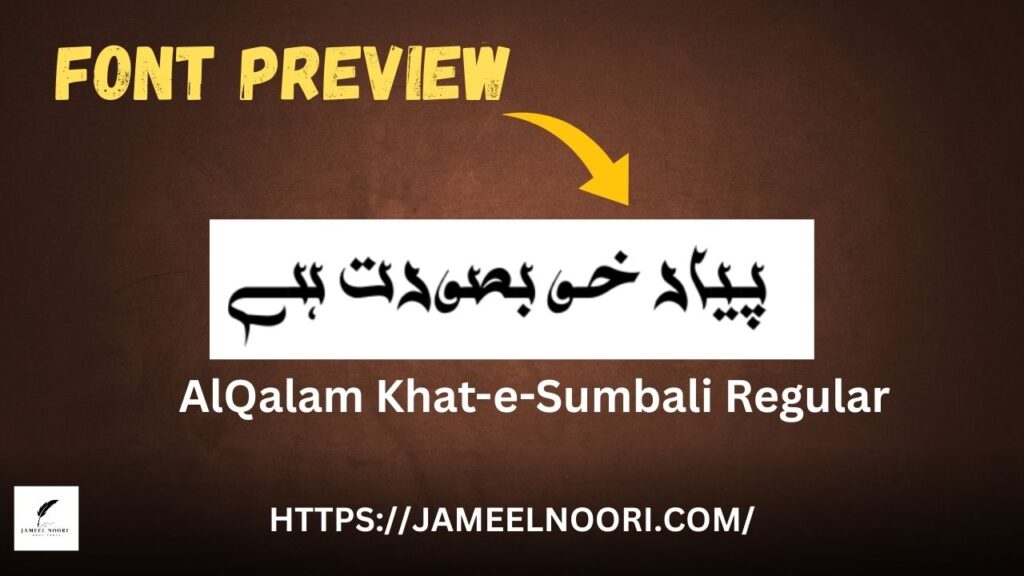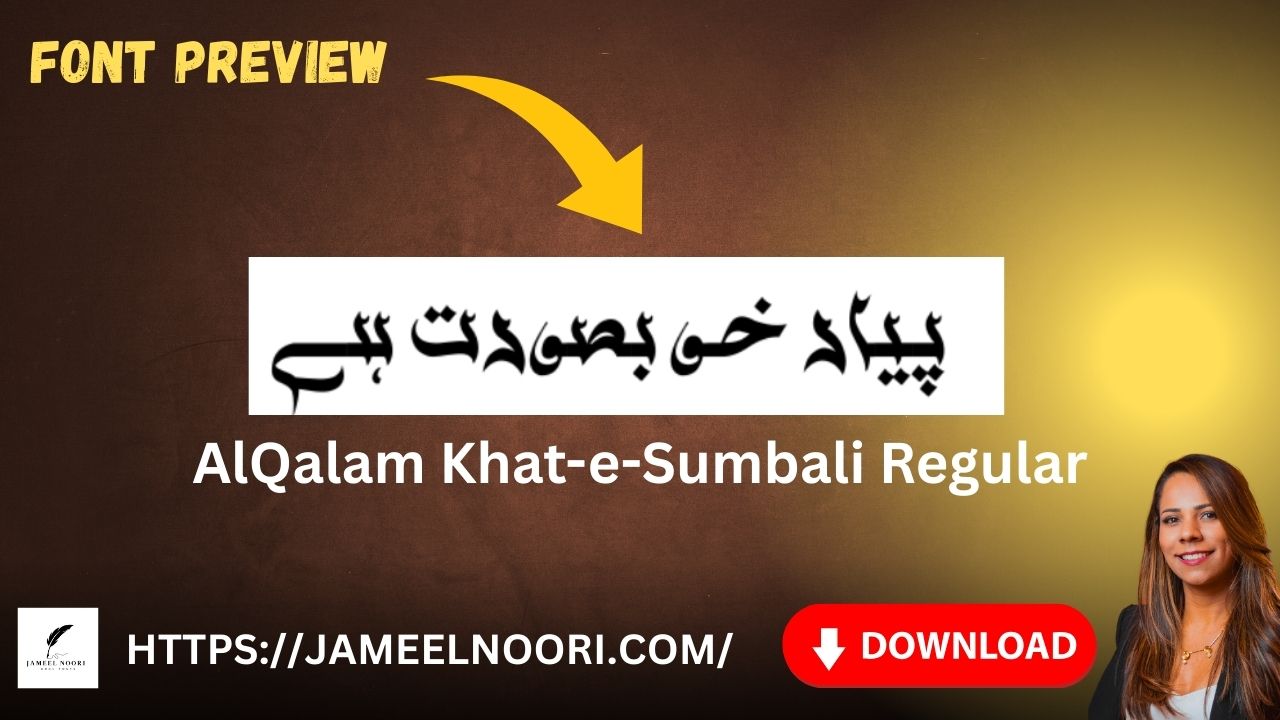
Urdu Font AlQalam Khat-e-Sumbali aik bohat hi popular aur elegant Urdu font hai jo specially designers, writers aur Urdu content creators ke liye design kiya gaya hai. Ye font not only professional look deta hai balkay readability aur style dono ko balance karta hai. Is article me hum apko is font ke bare me complete information dy gy taki aap bina time waste kiye is font ka best use kar saken.
What is Urdu Font AlQalam Khat-e-Sumbali?
Urdu Font AlQalam Khat-e-Sumbali aik Regular TrueType font hai jo Urdu likhne walon ke liye best choice mani jati hai. Ye font AlQalam series ka part hai jo Pakistan me widely use hoti hai, khas taur par printing, designing aur official documents ke liye. Iska design calligraphy style me hai jo traditional aur modern dono touch deta hai.
Features of Urdu Font AlQalam Khat-e-Sumbali
Ye font clear curves, smooth alignment, aur perfect spacing provide karta hai jo Urdu text ko visually attractive banata hai.
Best Uses of Urdu Font AlQalam Khat-e-Sumbali
- Urdu Poster Designing
- Book Publishing
- News Headlines
- Urdu Poetry Writing
- Certificates and Invitation Cards
Ye font especially Karachi, Lahore, aur Islamabad ke graphic designers ke darmiyan popular hai kyunke ye professional aur graceful look deta hai.
Advantages of Using Urdu Font AlQalam Khat-e-Sumbali
- Traditional Urdu calligraphy style
- Excellent for print aur digital use
Comparison: AlQalam Khat-e-Sumbali vs Jameel Noori Nastaleeq
| Font Name | Style | Readability | Usage |
| AlQalam Khat-e-Sumbali | Elegant Regular | Easy | General Design |
| Jameel Noori Nastaleeq | Classic Nastaleeq | Medium | Newspapers, Books |
Tips to Use Urdu Font AlQalam Khat-e-Sumbali Effectively
- Font size 14 ya us se zyada use karein readability ke liye.
- Headings me bold version use karein taake impact zyada ho.
- Background light aur text dark rakhein for better contrast.
- Print documents me spacing properly adjust karein.
Urdu Font AlQalam Khat-e-Sumbali aik complete package hai un users ke liye jo Urdu writing me professional aur stylish look chahte hain. Ye font readability, beauty, aur compatibility ka perfect balance rakhta hai. Agar aap Pakistan me Urdu design ya writing ka kaam karte hain, to ye font aapke liye best choice hai.
What type of Font AlQalam Khat-e-Sumbali?
It is a Regular TrueType Urdu font designed for stylish and readable Urdu text.
What makes AlQalam Khat-e-Sumbali different from other Urdu fonts?
Its elegant and modern calligraphic design makes it unique.
Is this font suitable for printing purposes?
Yes, it’s ideal for books, posters, and certificates.
Can I use it for YouTube thumbnails or posters?
Yes, it’s perfect for graphic and digital designs.